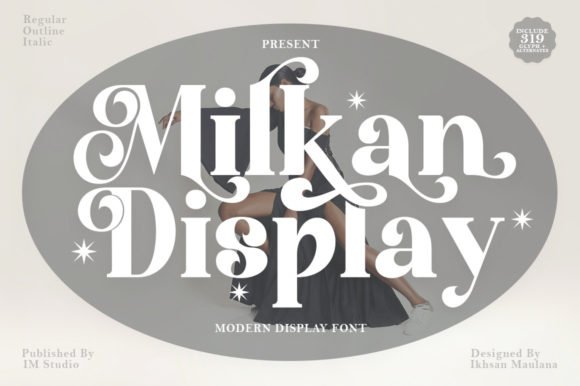
Milkan - это крутой и смелый шрифт с толстым начертанием.
Он потрясающе смотрится на свадебных приглашениях, благодарственных открытках, цитатах, поздравительных открытках, логотипах, визитных карточках и любом другом дизайне, который требует модного оттенка.